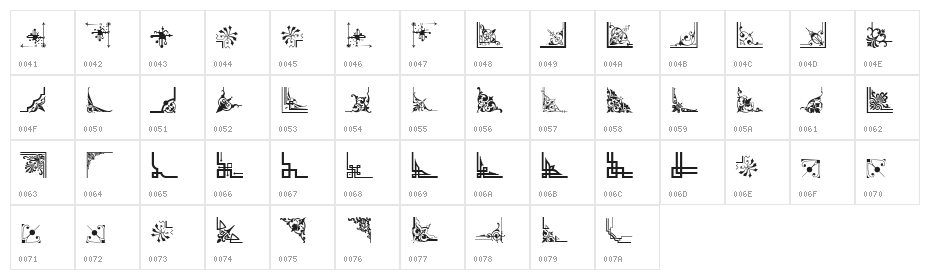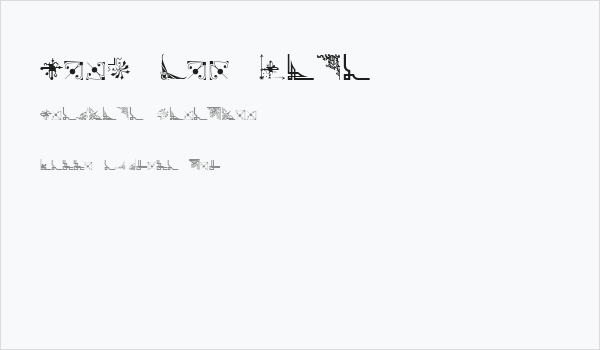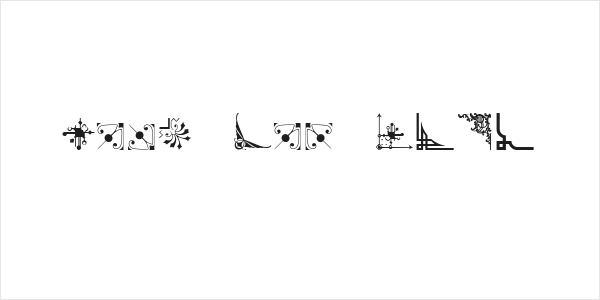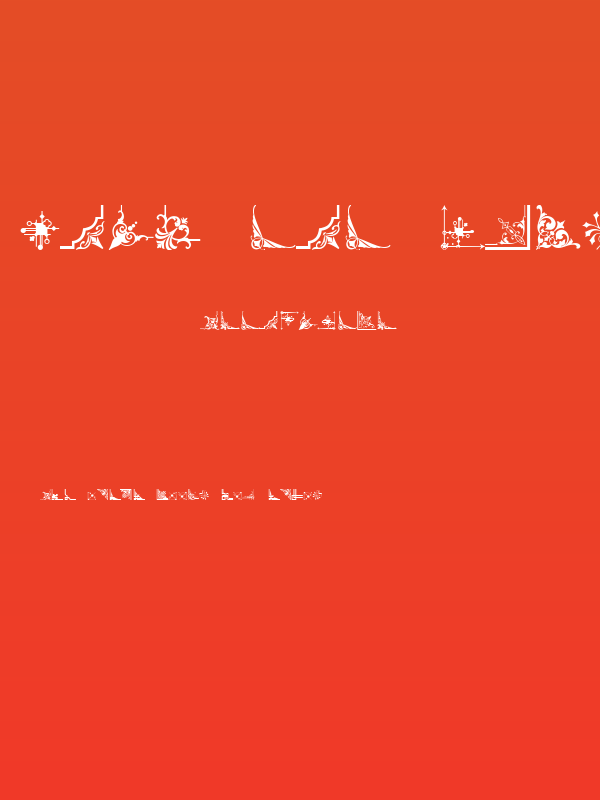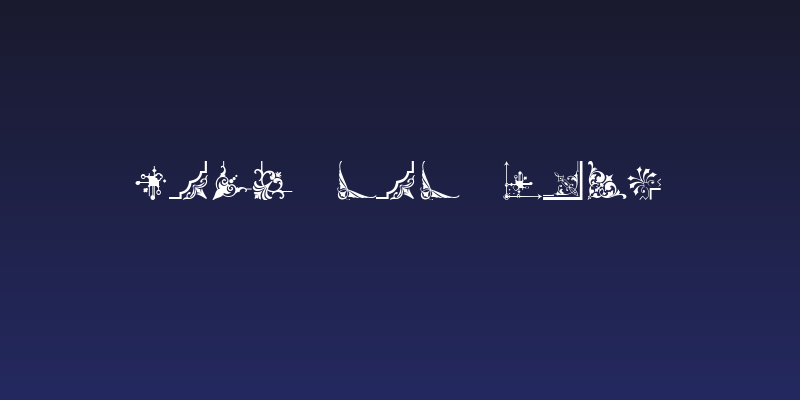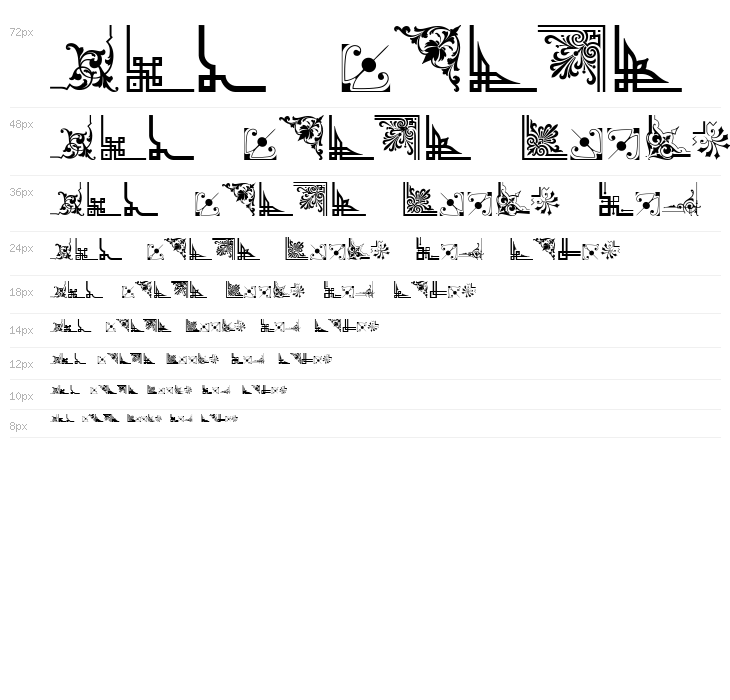
Corn Pop Five Font
Diese Schriftart enthält 54 Zeichen. Klicken Sie auf ein Zeichen für Details.
| Anwendungsfall | Borders, Frames, Decorative elements |
| Vorgeschlagene Projekte | These designs are perfect for use in invitations, certificates, decorative borders, and vintage-themed projects. |